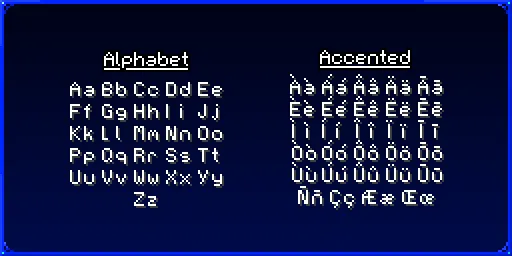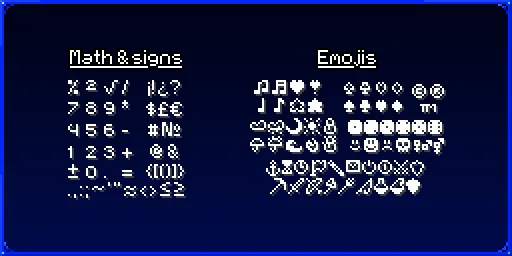
Главная фишка: ресурс-пак полностью меняет шрифт игры, делая буквы и цифры более гладкими и не такими растянутыми, чтобы читать чат, таблички и книги было проще и приятнее.
Что именно делает пак: он перерисовывает большую часть файлов ascii.png, accented.png и nonlatin_european.png. Алфавит стал ровнее и менее вытянутым, все цифры и большинство математических и пунктуационных знаков переработаны. Эмодзи почти не трогались — они уже хорошо выглядят. Также слегка доработаны кириллица и греческие символы, хотя подробных превью на них нет.
Польза для игрока простая: текст в интерфейсе, книгах, на табличках и в чате читается лучше, меньше мелкой визуальной мешанины при сборках и на серверах. Легкий ресрспак без лишнего - просто чистое улучшение шрифта, который подойдет в любом ресурспаке или сборке.
Текстура для шрифта, которая делает буквы, цифры и знаки более гладкими и аккуратными.